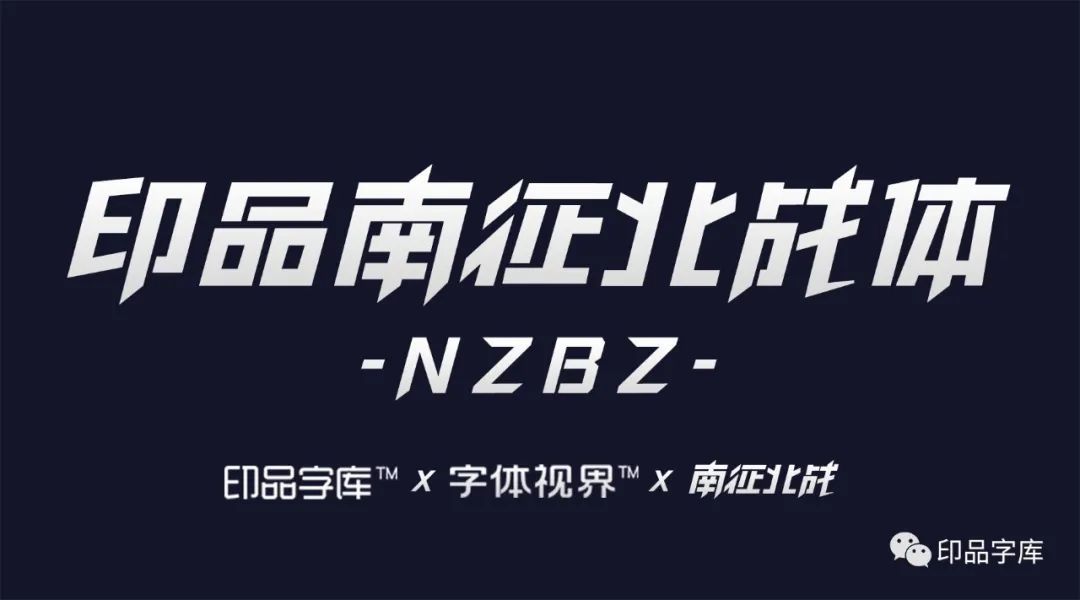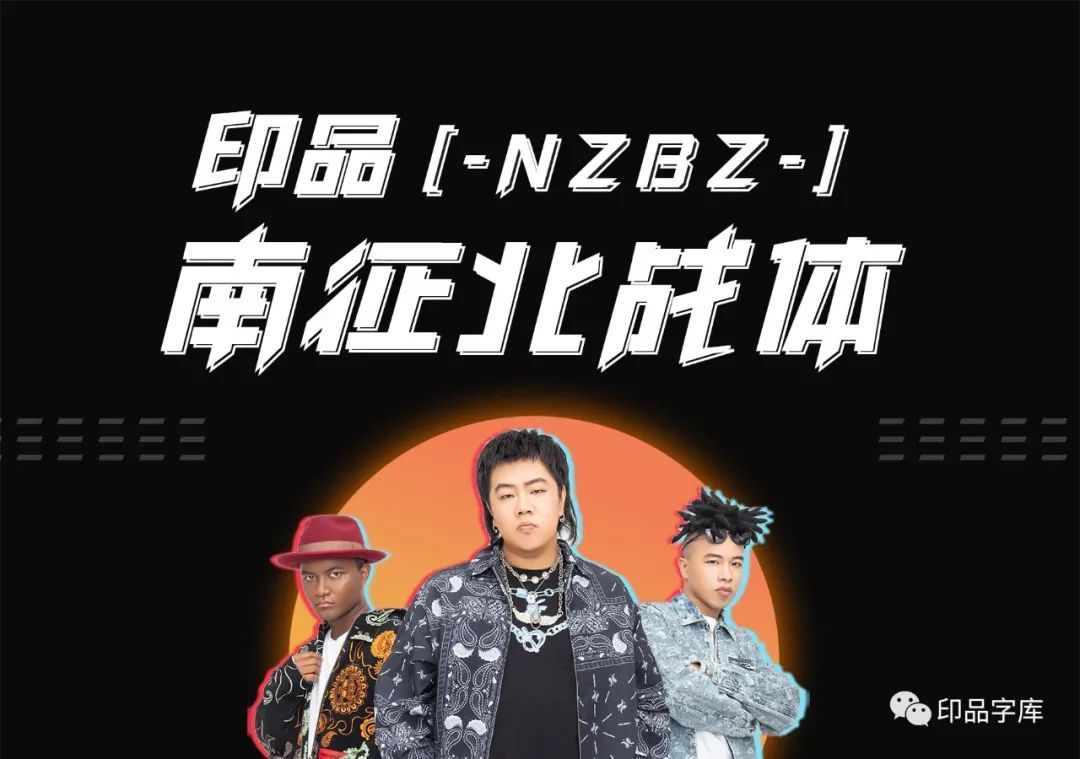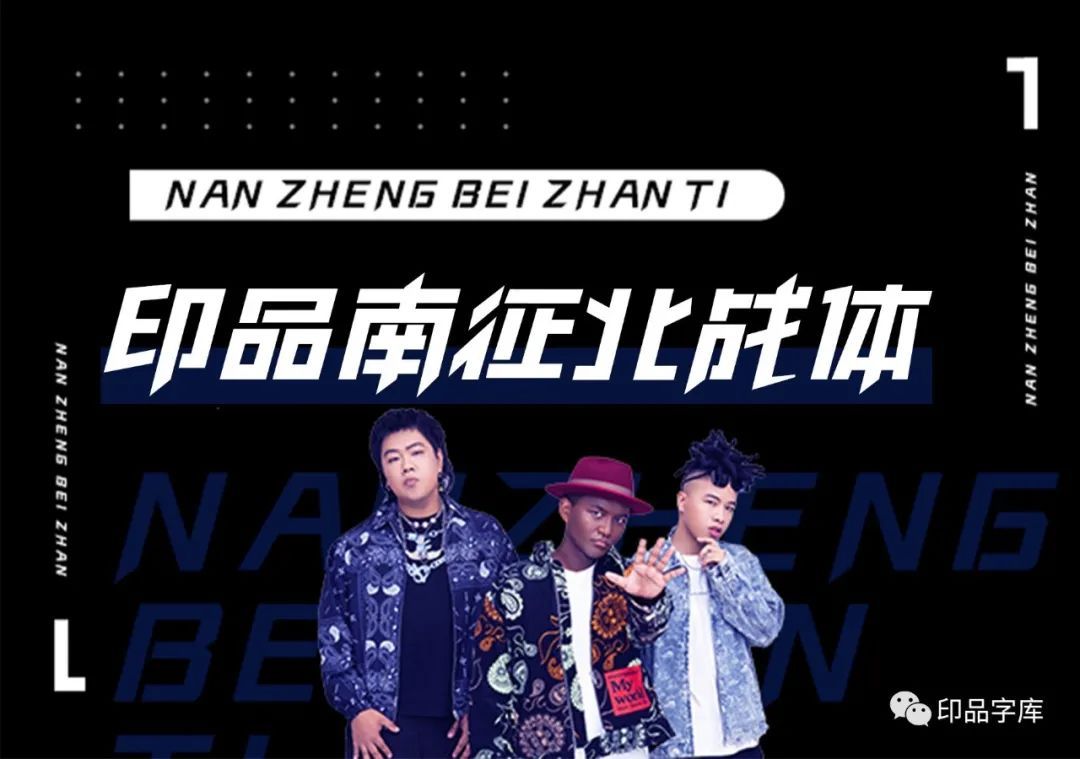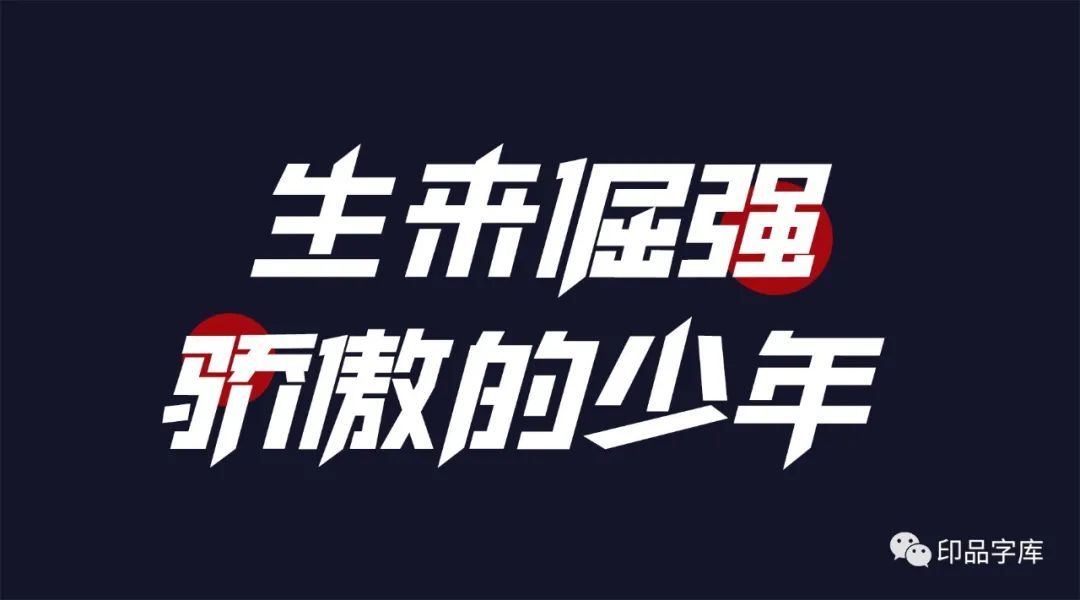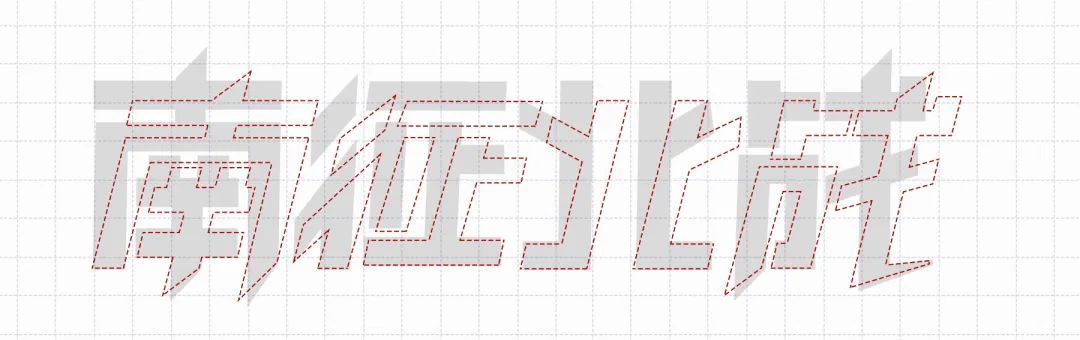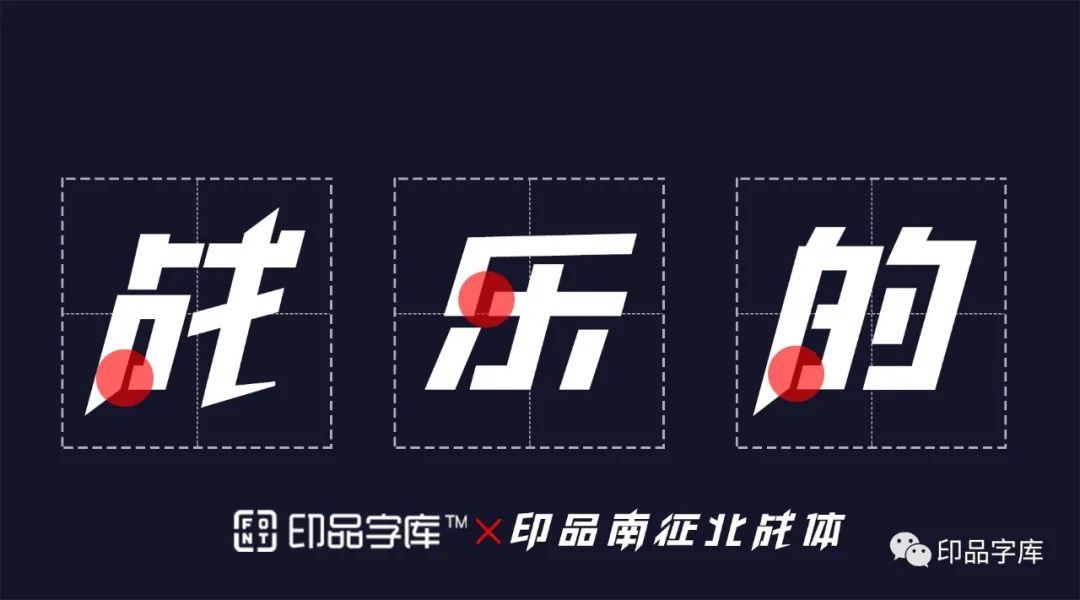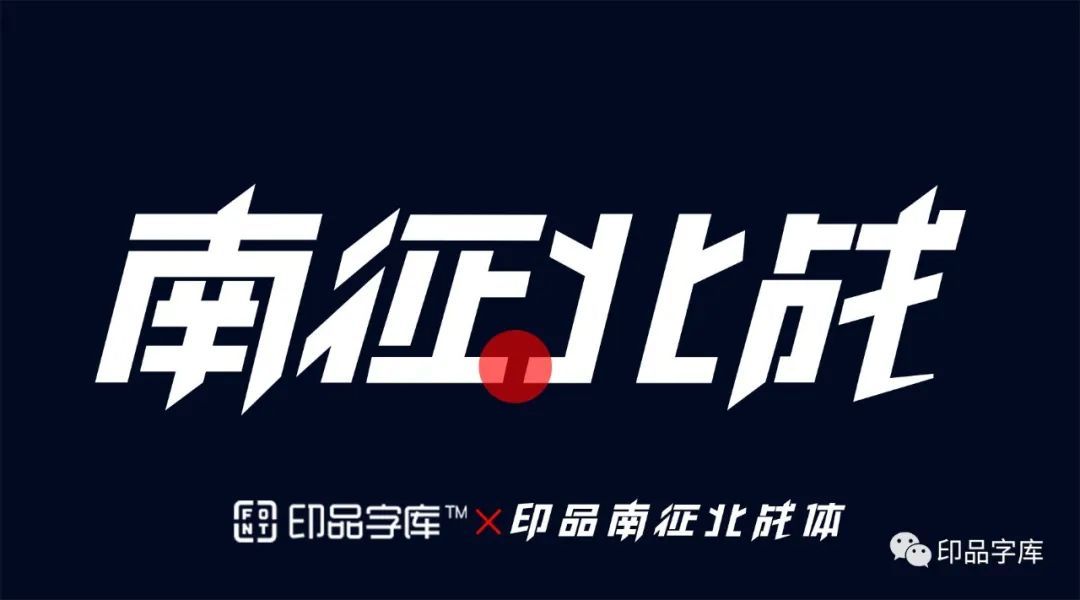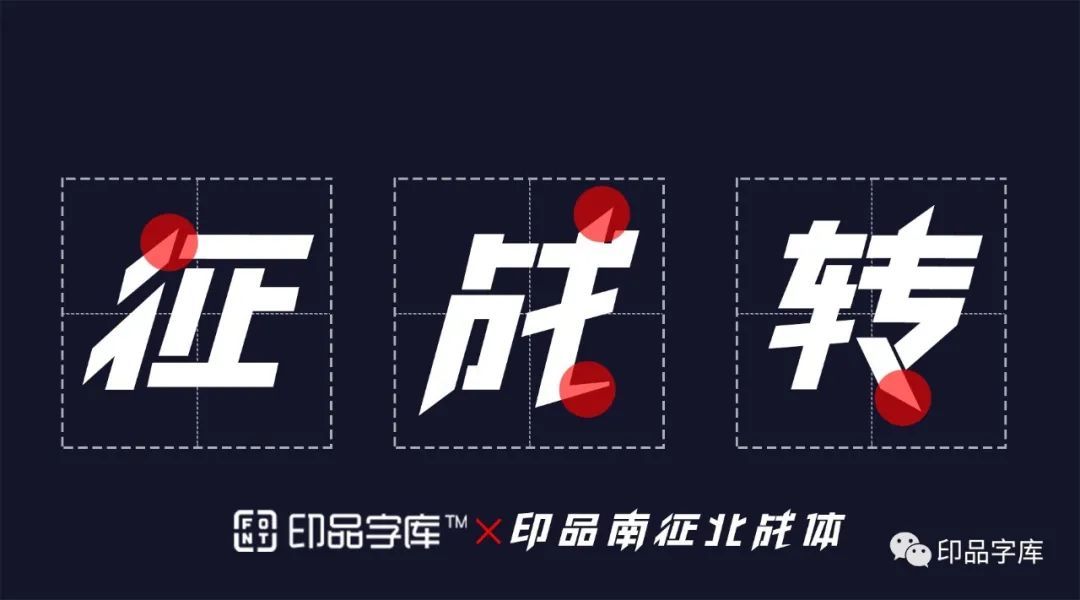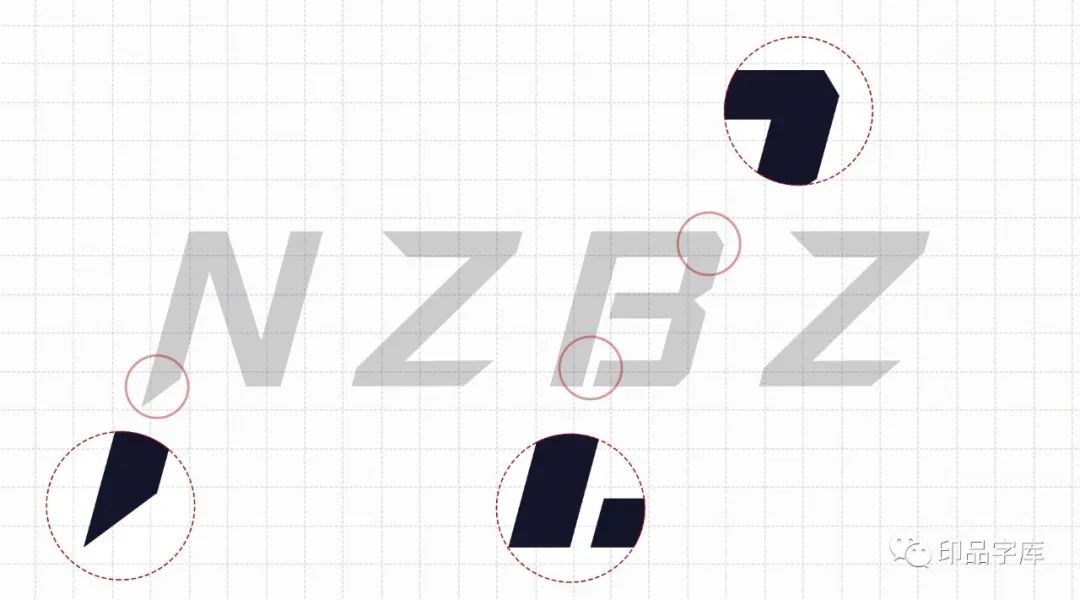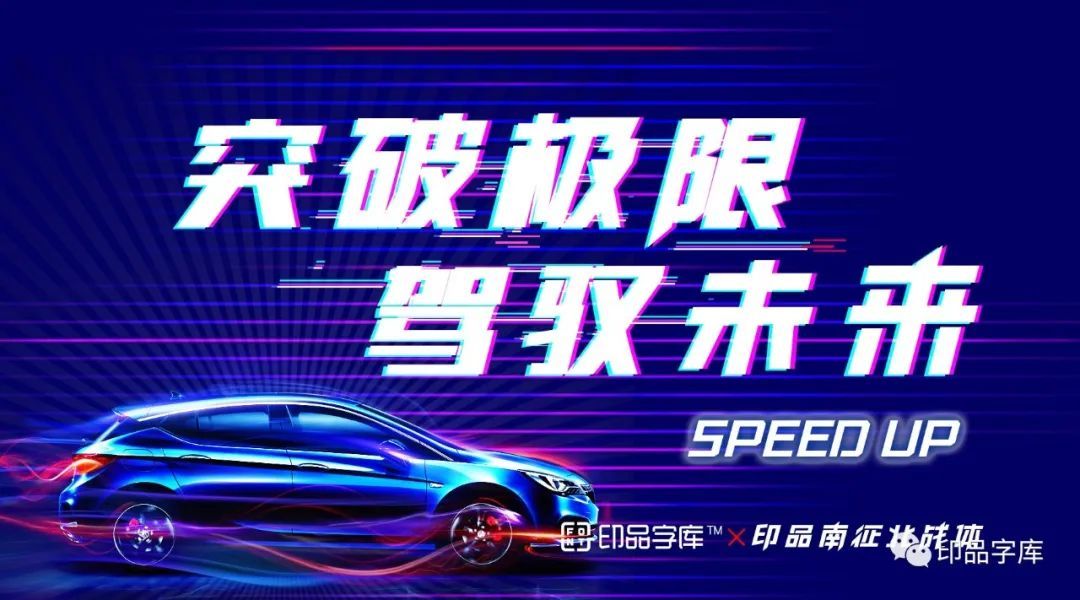
南征北战NZBZ,中国内地音乐组合,由汀洋、赵辰龙、尼成三名成员组成。南征北战NZBZ创造出V-Pop(Various Pop Music),即多元化流行音乐,制作出“南征北战NZBZ”式的流行表达,重新定位新一代的流行音乐。
2020年10月,南征北战作为开场嘉宾,在综艺节目《这就是街舞》第三季总决赛冠军之夜演唱歌曲《饕餮》、《不愿回头》等,诠释着“新一代流行音乐”,开幕式采用了全新品牌形象,南征北战与印品字库团队共同开发设计完成了全新品牌专属字体--------印品南征北战体也正式亮相。 在互联网时代,南征北战不在局限于传统音乐定位,全新品牌定位“V-Pop”,2020年8月,发型了第六张新EP《二十多岁》-将血气方刚,意气飞扬属于当代男儿的特点应用于音乐中,以音乐为戎,走南闯北,带领用户青春蔓延,携手共进。 为了更好的与智能时代下的粉丝进行互动沟通,诠释品牌定位,同时体现新品牌价值的主张与精神,南征北战将品牌形象进行了升级,以炫酷动感的视觉体验,结合奋斗的态度和专业的设计,融入到印品南征北战体的设计当中。 “印品南征北战体”基于南征北战全新定位“V-POP”,通过字体设计来表达“生来倔强”和“骄傲的少年”。 “南征北战”作为一个针对大众的一个明星组合,一本杂志的封面,字体设计要考虑两点因素:一是比较醒目,要在保证字体100%识别性的基础上进行设计;二是要符合南征北战的品牌定位。这类字体要气势感突出,视觉冲击明显,个性张扬有力,节奏分明,表现强烈的信心与勇气,给人以视觉上的震撼,双方团队通过反复沟通、碰撞,进行个性化的设计。 压扁倾斜,增加动感 进行了压扁和倾斜,以此来增加整组字的动感,像动物奔跑的时候一样整体压低身体,跑车更低矮的车身减小风阻系数有利于加速,文字的倾斜和压扁也是达到同样的效果,体现动感十足。 缺口的笔画设计 统一了字体特征,这个缺口使“战”的下部更加通透,也增加了整组字的家族特征。 横向笔画规划连接 把“征”和“北”进行了连接,做这种横向对比规划的时候,要主观地对其一些高度相近的横向笔画,让两个字相邻两个边的关系更紧密。 夸张的笔画,增加力度 利用字体周边的点进行衍生 笔画的细节上,通过延长笔画,突破原先字体水平线,在利用添加锚点、转换锚点、增加棱角的设计方法,可以使笔画更有力道,更具冲击力。 中西文匹配,强化品牌特征 为实现中西文匹配,满足品牌国际化需求,印品南征北战体西文采取了和中文一样的设计规则“压扁倾斜”的设计,折角处进行切角处理,以及延长笔画,缺口设计。 在整套“印品南征北战体”的西文设计中,“左直右切”的设计特征被大量应用,使得整个西文简约、时尚,气势感突出。 值得一提的是,在整个设计过程中,为避免字形过于圆润,对该结构的字体进行了“倾斜方形”处理,力量和速度的同时,增加了科技感。 全新的“印品南征北战体”以科技炫酷的视觉体验,增强了字体的跃动感,符合倔强少年不服输,奔跑的本意,为字体添加了野性,更符合这个南征北战音乐组合的本质。